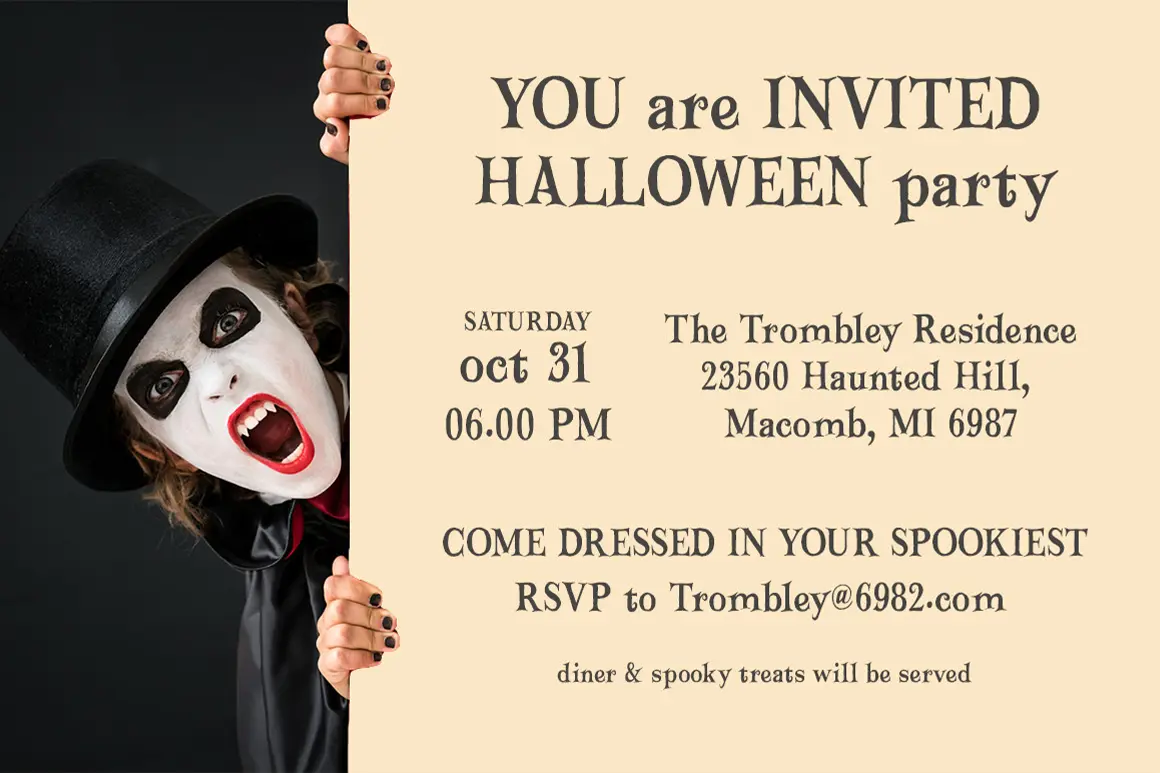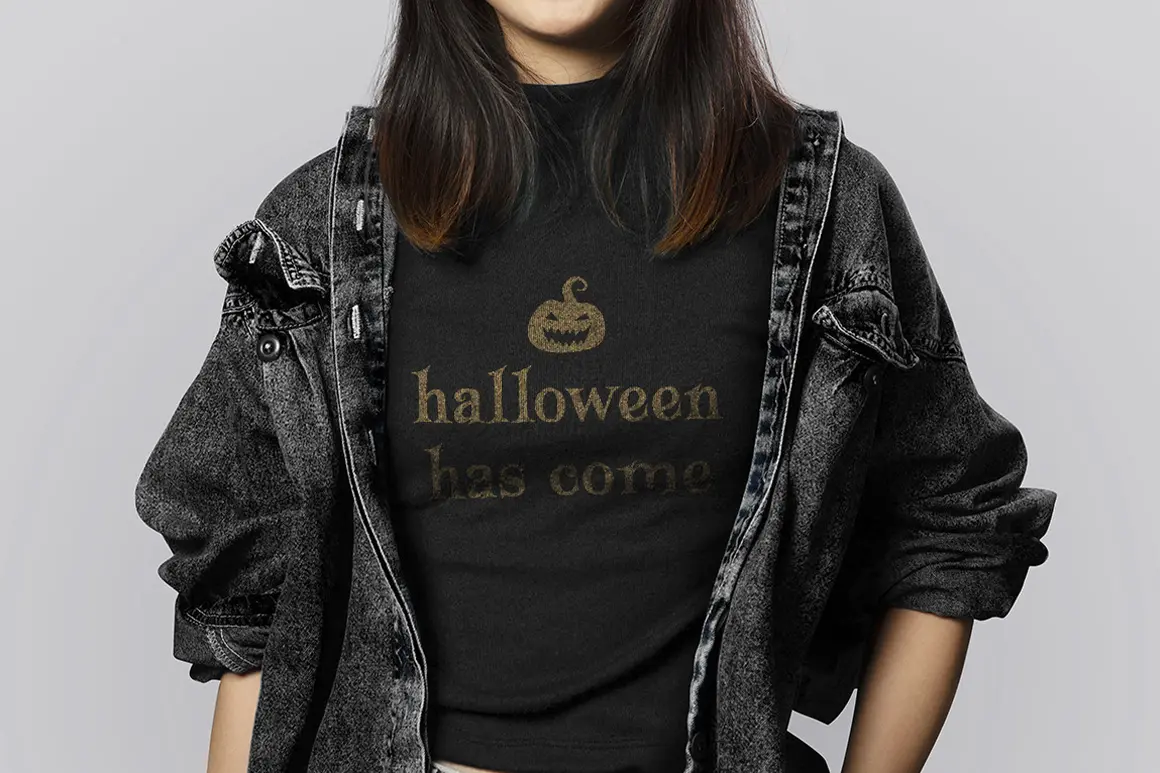
فونت فانتزی و ترسناک هالووین
فونت Happy Halloween یک فونت انگلیسی فانتزی و ترسناک با طراحی جذاب و بازیگوش است که برای پروژههای هالووین، طراحی پوستر، تراکت، لوگو، بنر و آثار گرافیکی مناسبتی کاربرد دارد.
Happy Halloween یک فونت نمایشی (Display Font) با طراحی خلاقانه، فانتزی و الهامگرفته از فضای هالووین است. این فونت با ظاهری سرگرمکننده و در عین حال ترسناک، انتخابی عالی برای انواع پروژههای گرافیکی مرتبط با جشن هالووین و مناسبتهای پاییزی به شمار میرود.
طراحی منحصربهفرد حروف در این فونت باعث میشود عناوین و نوشتههای شما جلوهای جذاب، متفاوت و حرفهای داشته باشند. اگر قصد طراحی پوسترهای هالووین، تراکتهای تبلیغاتی، دعوتنامه جشنها، کاور شبکههای اجتماعی، لوگو یا بنرهای مناسبتی را دارید، این فونت میتواند به بهترین شکل پیام شما را به مخاطبان منتقل کند.
فونت Happy Halloween با سبک خاص و خوانایی مناسب، برای استفاده در پروژههای چاپی و دیجیتال ایدهآل بوده و به طراحان کمک میکند تا ایدههای خلاقانه خود را با ظاهری جذاب و حرفهای اجرا کنند.
ویژگیهای فونت:
- طراحی فانتزی و ترسناک
- مناسب پروژههای هالووین
- سبک نمایشی (Display Font)
- ایدهآل برای تیترها و عناوین
- خوانایی مناسب در ابعاد مختلف
- مناسب استفاده چاپی و دیجیتال
- طراحی خلاقانه و جذاب
کاربردها:
- طراحی پوستر هالووین
- طراحی تراکت تبلیغاتی
- ساخت لوگو و تایپوگرافی
- طراحی بنرهای مناسبتی
- تولید محتوای شبکههای اجتماعی
- طراحی دعوتنامه جشنها
- بستهبندی محصولات فصلی
- پروژههای گرافیکی فانتزی